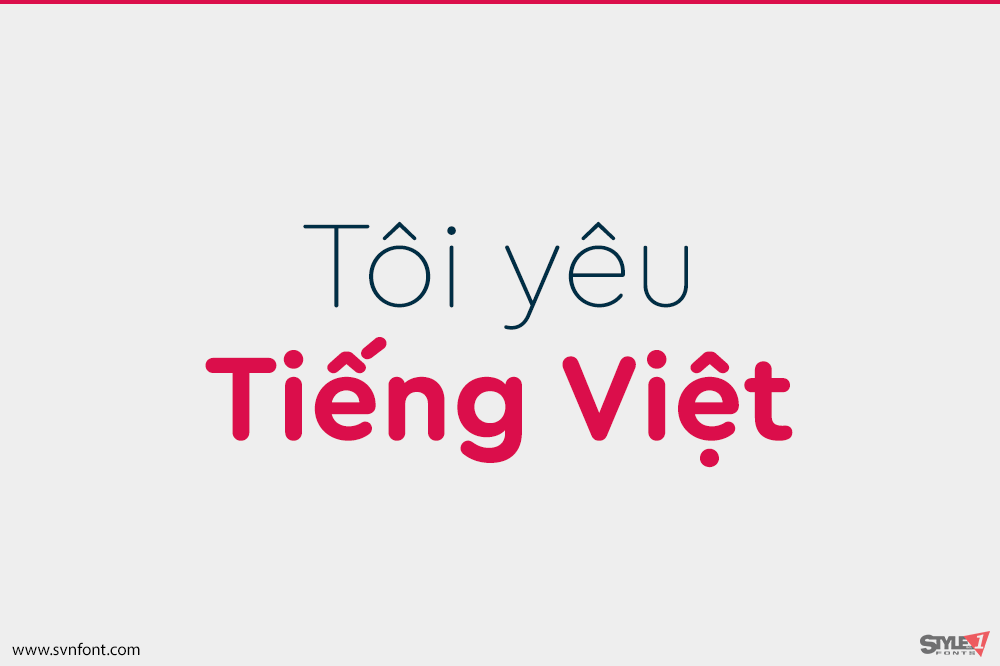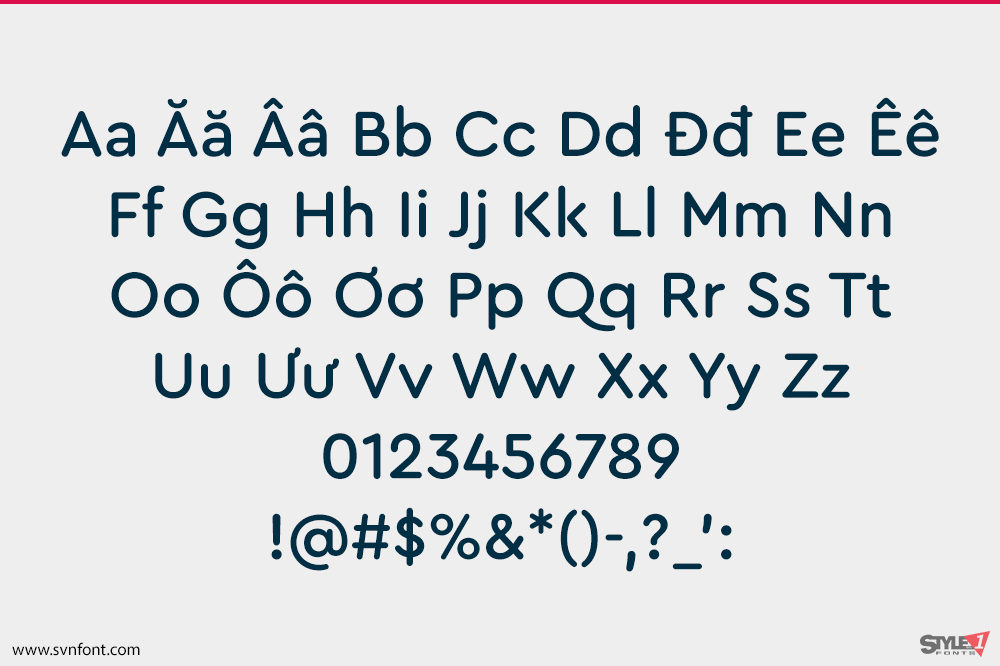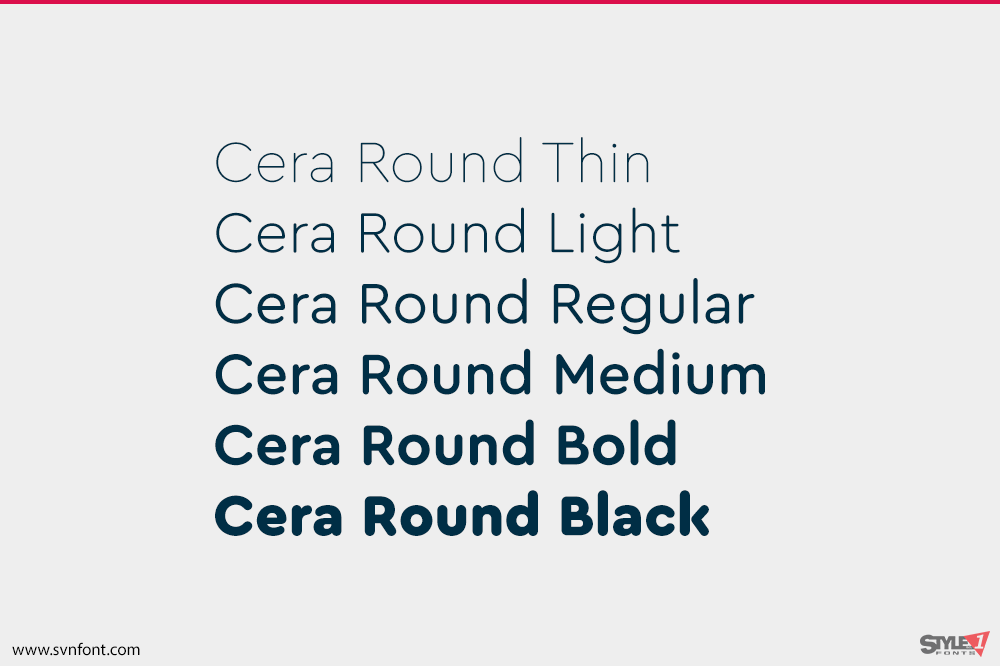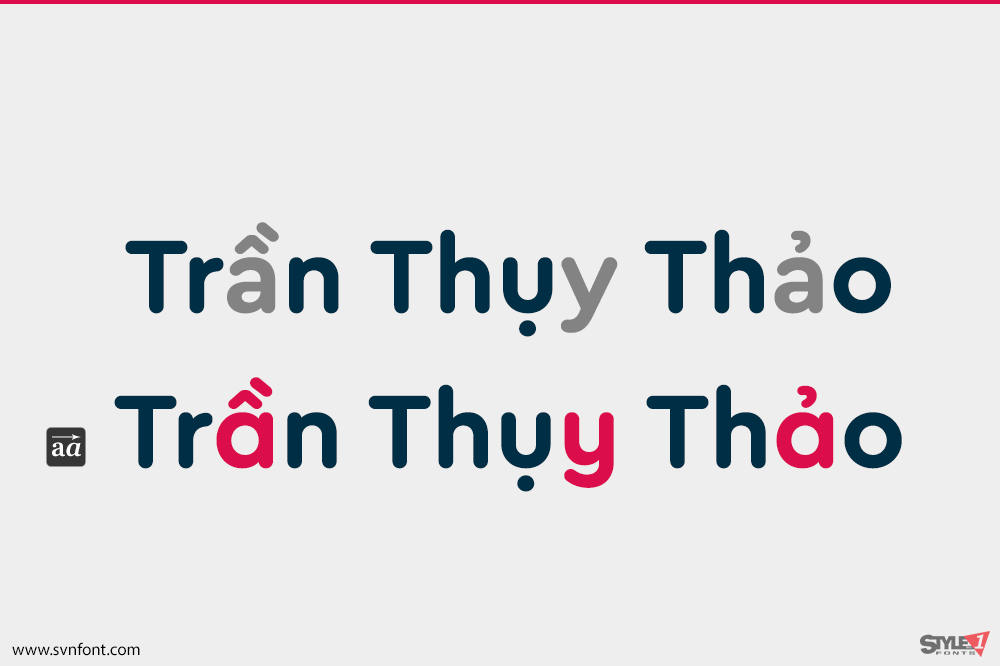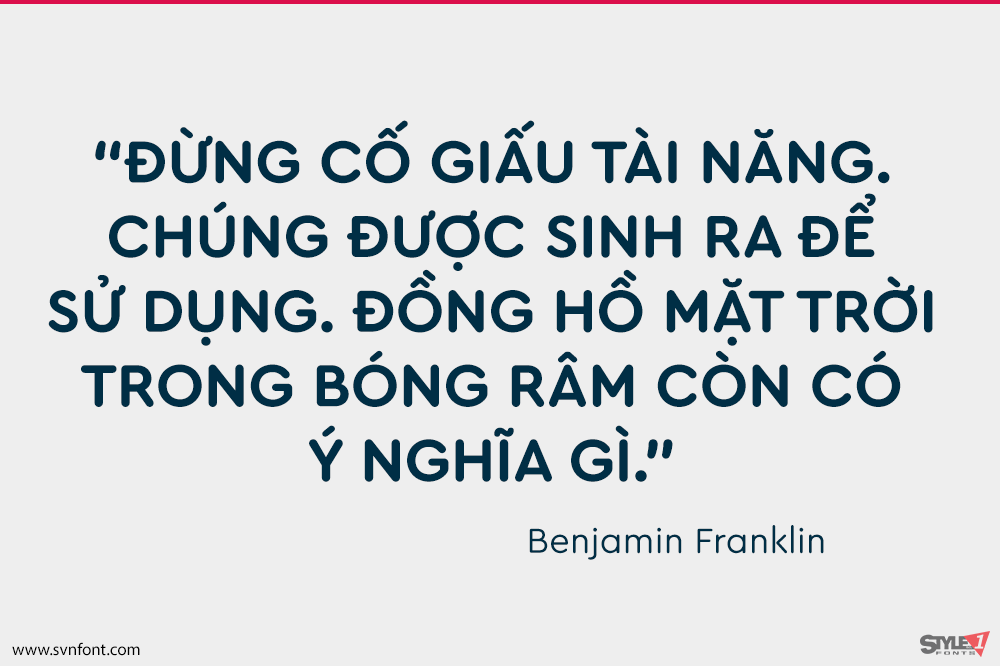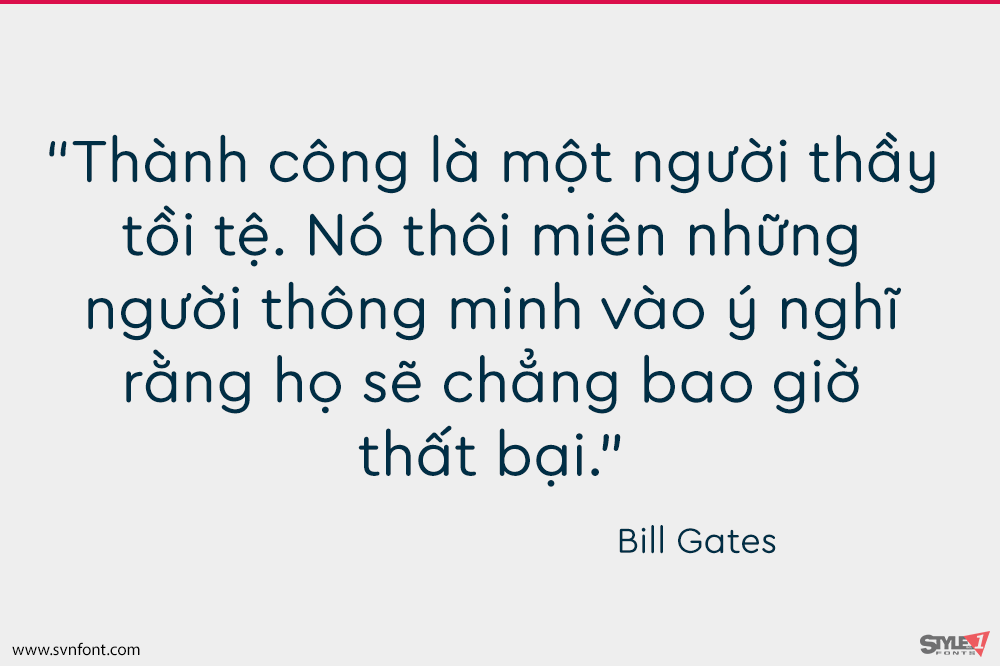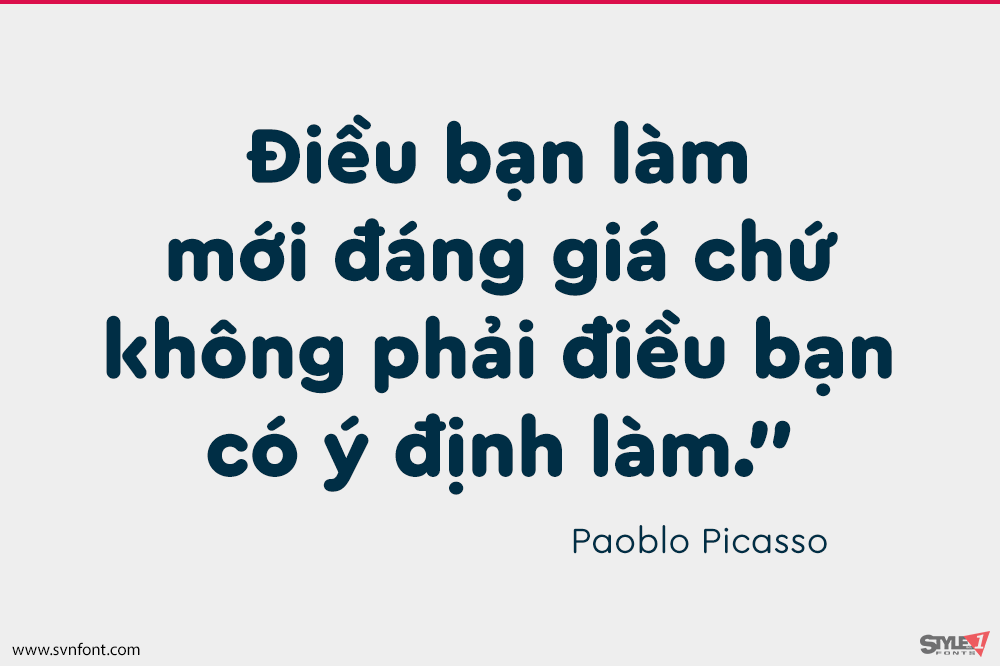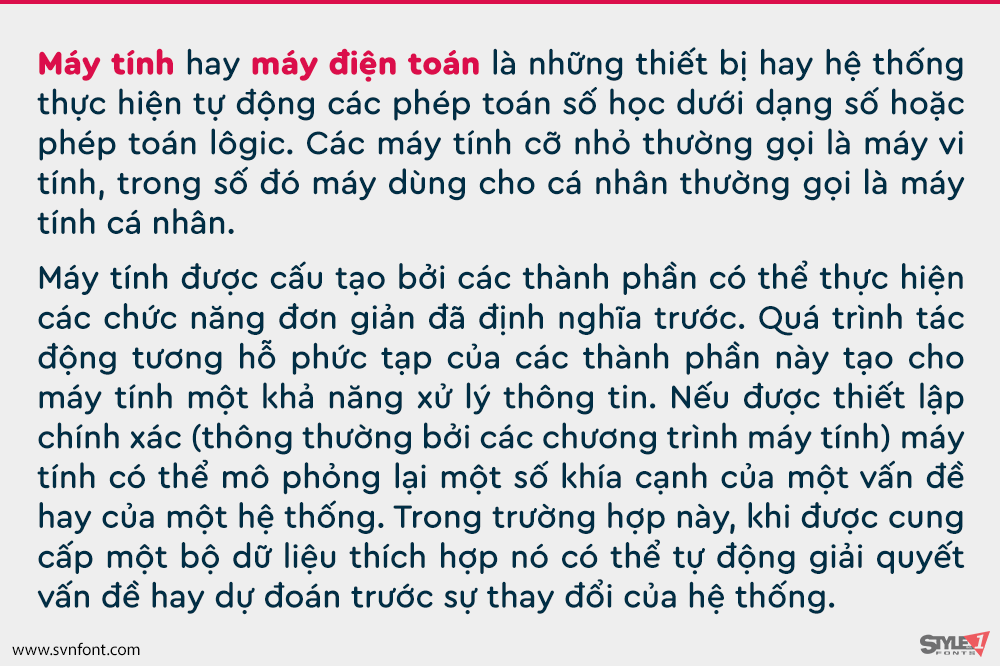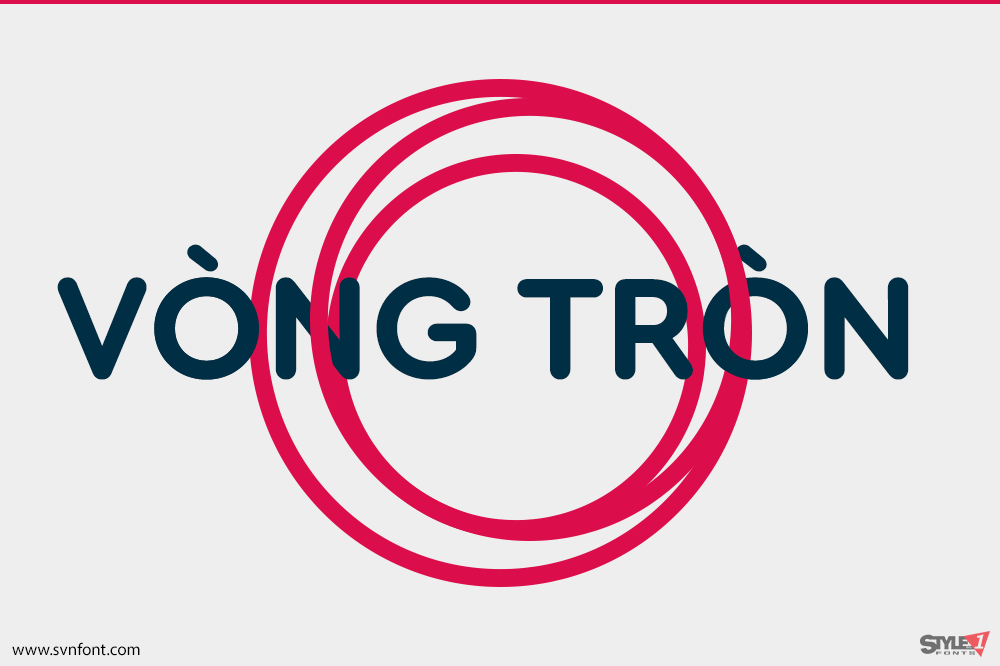
Với sức mạnh tương đương các thành viên khác trong bộ sưu tập, Cera Round Pro kết hợp sự ấm áp với nét thanh lịch, và khả năng hỗ trợ chữ Cyrillic và Hy Lạp khiến nó trở thành một người bạn đồng hành đáng tin cậy và hấp dẫn cho giao tiếp quốc tế.
Dựa trên truyền thống của kiểu chữ được phay bằng máy và kết hợp với hình học kỹ thuật của phông chữ Cera, Cera Round Pro có các đầu nét tròn và các góc bo mềm mại để tạo ra một cảm giác vui tươi cho văn bản. Trong số các hình dạng chữ mượt mà nhưng chính xác của nó, chữ “o” tròn mang một nét nổi bật mới.
Trong khi kiểu chữ regular đã được kiểm tra kỹ lưỡng cho các văn bản biên tập dài, sáu độ đậm của Cera Round Pro, từ thin đến black, cho phép thể hiện toàn bộ dải cảm xúc trong kiểu chữ trang trí. Nếu các độ đậm mỏng mang sự gọn gàng và chính xác của bản vẽ kỹ thuật, thì các độ đậm nặng lại vui tươi và mềm mại: hoàn hảo cho các tiêu đề mạnh mẽ và các dự án bao bì. Với dải biểu cảm rộng như vậy, từ tính kỹ thuật đến sự thân thiện — và luôn chân thành — Cera Round là một lựa chọn tuyệt vời cho thiết kế thương hiệu và biên tập. Chiều cao x-height lớn của nó cũng làm cho nó được khuyên dùng cho thiết kế giao diện.
Và mặc dù Cera Round Pro có thể là một phiên bản đối lập với Cera, nó không chỉ đơn giản là Cera với các góc bo tròn. Chúng tôi đã cẩn thận chỉnh sửa và điều chỉnh nhiều ký tự để phù hợp với thái độ mới của Cera. Khi các cạnh bo tròn và hình dạng mượt mà tạo ra các vấn đề quang học mới, chúng tôi đã tìm ra những giải pháp mới: biến Cera Rounded Pro trở thành một thành viên độc lập của Bộ sưu tập Cera.
Ngoài tiếng Latinh, Cera Round hỗ trợ tiếng Hy Lạp và Cyrillic với các biến thể địa phương hóa và như mọi khi, nó được trang bị một số tính năng in ấn bổ sung: số dạng bảng, phân số tùy ý, các biểu tượng hữu ích và dingbats.
Nhà thiết kế: Jakob Runge, Lisa Fischbach